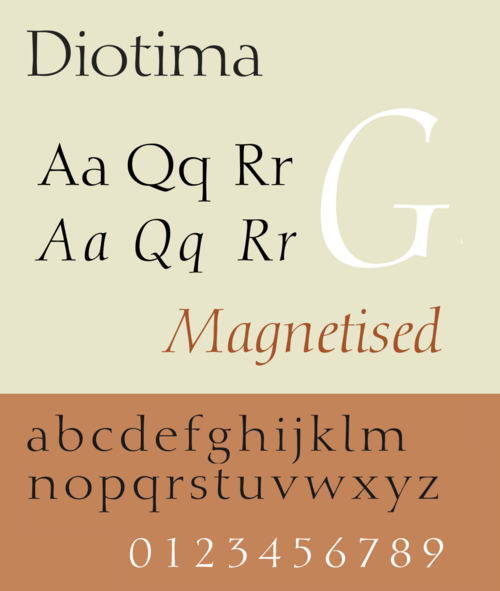
| カテゴリ | セリフ 表示 |
| デザイナー | グドルン・ツァップ=フォン・ヘッセ |
| 鋳造所 | ステンペル ライノタイプ |
| リリース日 | 1951年頃 |
Diotimaは、グドルン・ツァップ=フォン・ヘッセがデザインし、Stempel社が出版したセリフ 書体である。[a] [1]
ディオティマは比較的細身で幅広のデザインで、色が薄く、本文よりも装飾的な印刷や見出しなどの用途に適している。[2] [3] [4]ローマン体の外観は、トラヤヌス記念柱にあるようなローマ時代の角張った大文字を思い起こさせ、例えば「M」の上部にセリフがない(イタリック体にはセリフがある)などである。イタリック体の小文字は比較的カリグラフィ風のデザインで、「g」は「1階建て」である。このデザインは哲学者マンティネイアのディオティマにちなんで名付けられており、おそらく、この時点までに女性によってデザインされた数少ない書体の一つとしての地位を適切に強調しているのかもしれない。
ディオティマは、ローマン体またはレギュラー体で1951年頃に、イタリック体で1953年頃にリリースされましたが、この時点ではツァップ=フォン・ヘッセは数年にわたってデザインに取り組んでいました。 [5] [6] [7]このデザインは彼女の最初の完全な書体でした。[8]彼女の夫であるヘルマン・ツァップは、結婚のお知らせの組版にこの書体を使用しました。[9]
当時のステンペルの作品では一般的だったように、オリジナルのリリースはパンチカッターのオーガスト・ローゼンバーガーによって作成されました。ステンペルは後に、それを補完するスワッシュ大文字のセットであるAriadne-Initialen (Ariadne Initials) をリリースしました。このデザインは後にLinotypeによって再リリースされました。
2001年、サンフランシスコ公共図書館はヘルマン・ツァップとグドルン・ツァップの作品展を開催し、ディオティマの初期の標本を展示した。[10]
デジタル化
Diotima は、デジタルフォント時代の早い段階でデジタル化され、Linotype (Stempel から権利を継承) とAdobeによってリリースされました。
2008年から2009年にかけて、ライノタイプのツァップ・フォン・ヘッセと小林明は、新たな解釈であるディオティマ・クラシックをリリースした。この書体は、ライト、レギュラー、ボールド、ヘビーウェイト、イタリック体がある。[11]ライノタイプは、「レギュラー」ウェイトはインクが広がった後の金属活字に対応し、ライトは以前のデジタル版(右図)に類似していると説明した。[12]ボールドとヘビーウェイトは新たに追加された。幅はローマン体では若干狭くなり、イタリック体では広くなった。[1]